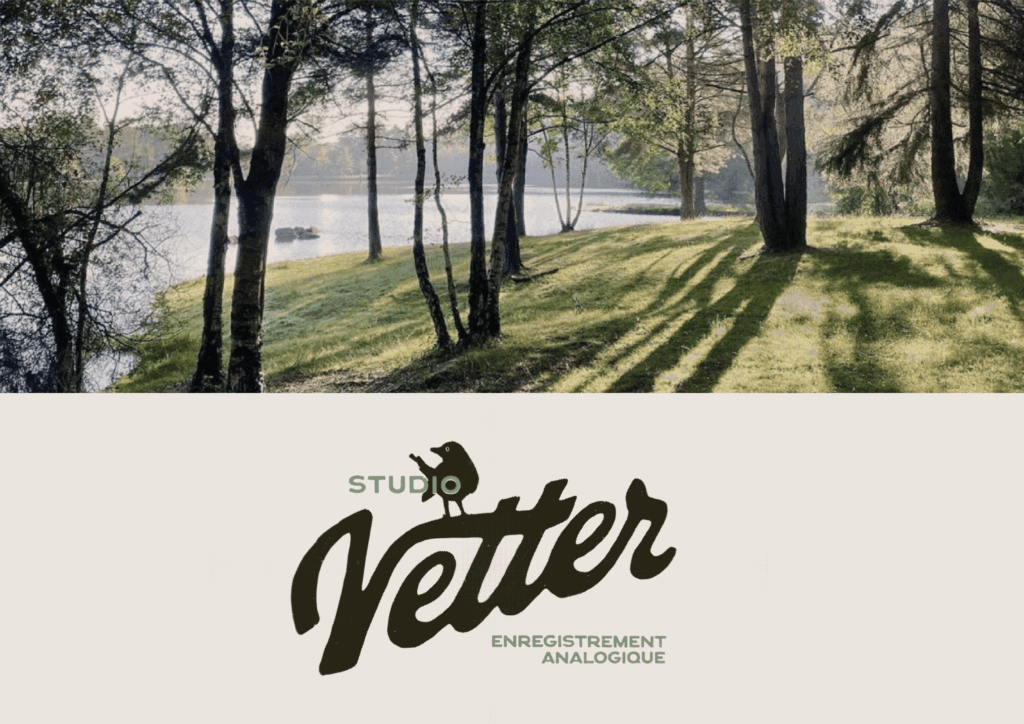
Capturez l'essence du son
Le Studio Vetter, est un studio d’enregistrement situé en pleine nature à Brocéliande. Jérôme m’a confié la refonte complète de l’identité visuelle avec l’objectif de capturer l’essence de ce lieu dédié à la création musicale.
L’idée était d’affirmer le positionnement du studio en mettant en lumière l’atmosphère inspirant, authentique ainsi que l’expertise technique et qualitatif que propose le lieu. Cette refonte visait à marqué le style du studio et à renforcer sa notoriété sur son marché.
Le résultat est une création sur-mesure et chargée de sens, qui traduit l’essence même du studio : un espace dédié à la créativité et à l’expérimentation sonore, où chaque artiste peut s’exprimer librement. Le lettrage et l’identité visuelle s’intègrent parfaitement à l’univers, mettant en avant la nature, l’humain, et la liberté artistique qui font la force du studio Vetter.